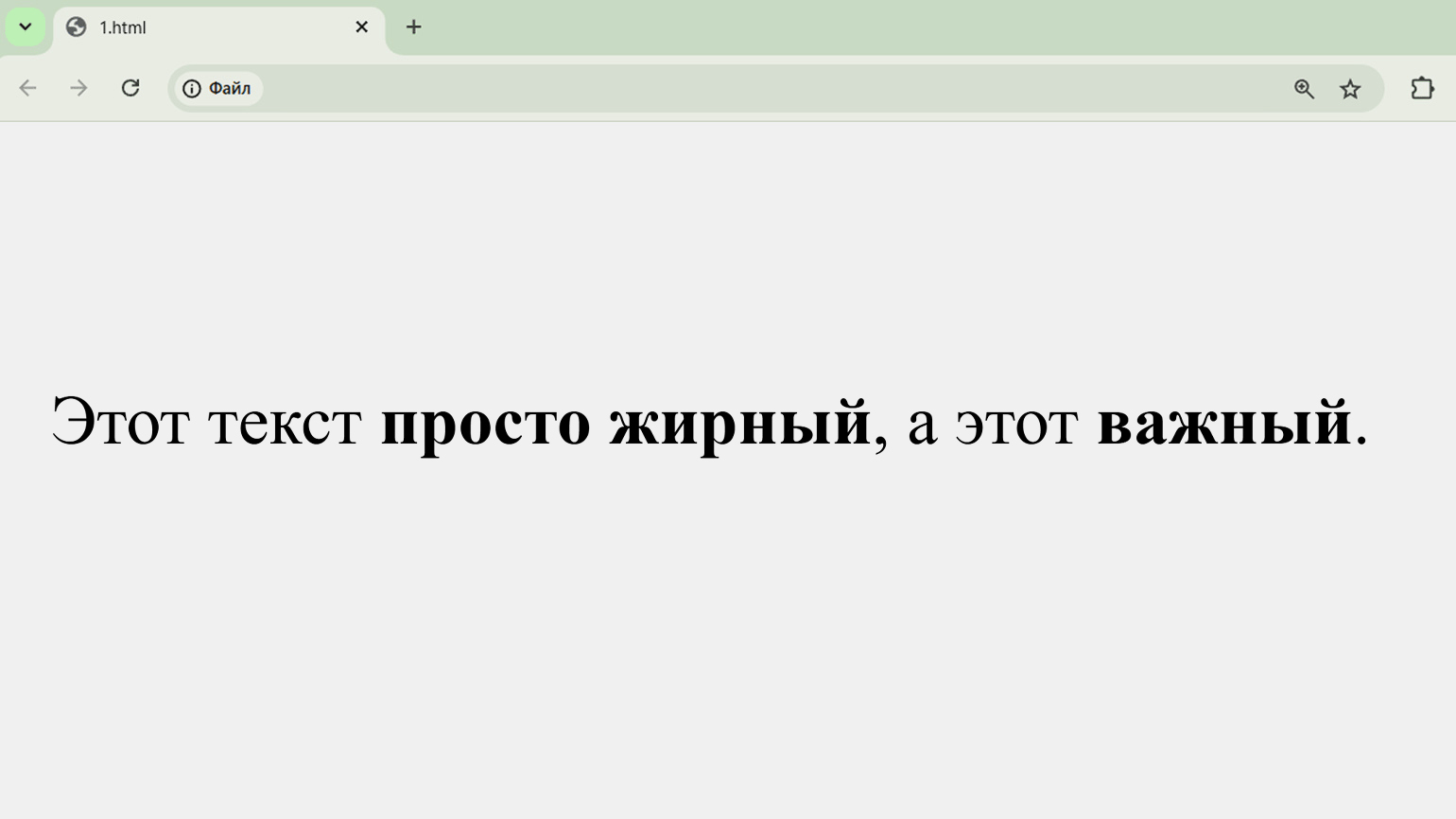
Жирный шрифт в HTML: как использовать тег <​b​> правильно
Разбираемся, как работает этот тег, когда его стоит применять и почему иногда лучше выбрать другой способ.
Тег <b> (от англ. bold — «жирный») используется в HTML для визуального выделения текста жирным начертанием. Он не добавляет тексту дополнительный смысл, а лишь акцентирует внимание читателя на контенте. В этой статье мы разберём, как работает этот тег и чем он отличается от других способов выделения.
Как работает тег <b> и зачем он нужен
Тег <b> делает шрифт в выделенном тексте жирным, чтобы он стал заметнее на странице. Поисковые системы и скринридеры (программы, читающие текст вслух людям с нарушением зрения) такое выделение игнорируют. Чтобы сообщить им, что это важный текст, на который стоит обратить внимание, используются другие методы. Мы поговорим о них ниже.
Тегом <b>, можно выделить, например:
• название товара или бренда;
• текст на кнопке;
• первые слова в пунктах списка, чтобы визуально отделить их друг от друга.
<p>Это обычный текст, а <b>это жирный шрифт</b>.</p
На странице выделится только фраза «это жирный шрифт».
Как правильно писать и использовать тег <b> в HTML-документе
Тег <b> — парный, то есть его нужно открыть (<b>) и потом закрыть (</b>). Всё, что находится внутри, будет отображаться в жирном начертании.
<p>Для запуска программы нажмите <b>Старт</b>.</p>
Браузер изменяет выделенный таким образом текст, применяя стиль font-weight: bold.
У тега нет своих уникальных атрибутов, но он поддерживает общие HTML-атрибуты:
• class — для подключения CSS-стилей;
• id — для уникальной идентификации;
• style — для быстрой настройки внешнего вида;
• title — всплывающая подсказка.
<b class="highlight" title="Важная информация">Обратите внимание!</b>
Что здесь происходит:
• class="highlight» — подключает CSS-класс с именем highlight, с помощью которого можно задать стили (например, цвет, отступы и так далее) в CSS-файле;
• title="Важная информация» — если навести курсор мыши на текст, появится всплывающая подсказка с этой фразой.
Тег <b> и тег <strong>: в чем разница
<strong> — похожий тег для выделения текста. Оба тега делают шрифт жирным, но работают по-разному:
• Тег <b> просто выделяет текст внешне, без дополнительного смысла.
• Тег <strong> показывает, что текст важный и что на него нужно обратить внимание. Это понимают и браузеры, и поисковики, и скринридеры (программы, которые читают текст вслух). Тегом <strong> можно выделить, например, предупреждения, ключевые фразы.
<p>Этот текст <b>просто жирный</b>, а этот <strong>важный</strong>.</p>
Внешне результат работы этих тегов выглядит абсолютно одинаково:
Как тег <b> влияет на доступность и SEO
Поисковые системы игнорируют тег <b>, потому что он не имеет смысла, то есть этот тег никак не влияет на SEO.
Сам по себе тег <b> не помогает и создать доступную среду для людей с нарушениями зрения, но его можно использовать вместе с ARIA-атрибутами. Тогда текст начнёт взаимодействовать со скринридерами.
ARIA-атрибуты помогают объяснить смысл текста программам для чтения с экрана. Это важно, если вы используете <b> и хотите, чтобы выделение было понято правильно.
Атрибут aria-label задаёт текстовую подсказку, которую скринридеры озвучивают вместе с содержимым элемента.
<p>Скорость автомобиля: <b aria-label="критически высокая"> — 200 км/ч</b></p>
Скринридер озвучит:
«Скорость автомобиля критически высокая — 200 километров в час».
Атрибут aria-hidden поможет спрятать текст от скринридеров:
<p>Это <b aria-hidden="true">важное</b> сообщение.</p>
Скринридер прочитает только: «Это сообщение» — слово «важное» будет пропущено, но визуально останется на экране.
Применение стилей вместо тега <b>
Если вам нужно просто выделить текст жирным, необязательно использовать тег <b>. Можно сделать то же самое с помощью CSS — языка, который управляет внешним видом страницы.
<p>Это <span class="highlight">выделенный</span> текст.</p>
.highlight {
font-weight: 700;
}
Здесь шрифт у выделенной фразы внутри тега <span> будет жирным, потому что мы задали стиль font-weight: 700 — то есть указали толщину шрифта 700. Лучше использовать числовое значение, а не значение bold, потому что современные шрифты поддерживают разные толщины:
НазваниеТолщина
Thin / Hair100
Extra Light200
Light300
Regular400
Medium500
Semi Bold600
Bold700
Extra Bold800
Black / Heavy / Ultra900
Используя числа, вы точно настраиваете внешний вид текста. Это важно, если у вас есть дизайн-макет или нужен единый стиль.
У стилей есть несколько преимуществ перед тегом <b>:
• Можно управлять стилем в одном месте — меняете стиль в CSS, и он применяется ко всем нужным элементам.
• Легко использовать разные типы выделения — жирный (font-weight), цветной (color), подчёркнутый (text-decoration) и другие.
• Код становится чище — структура (HTML) и оформление (CSS) разделены.
Зато тег <b> можно использовать:
• для быстрого выделения текста в небольшом фрагменте;
• если нет доступа к CSS (например, в CMS или конструкторе сайтов);
• в учебных примерах или черновиках.